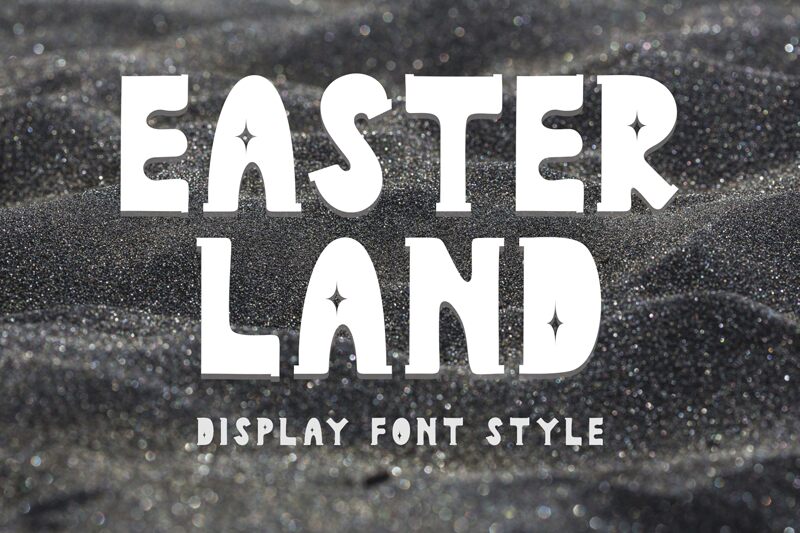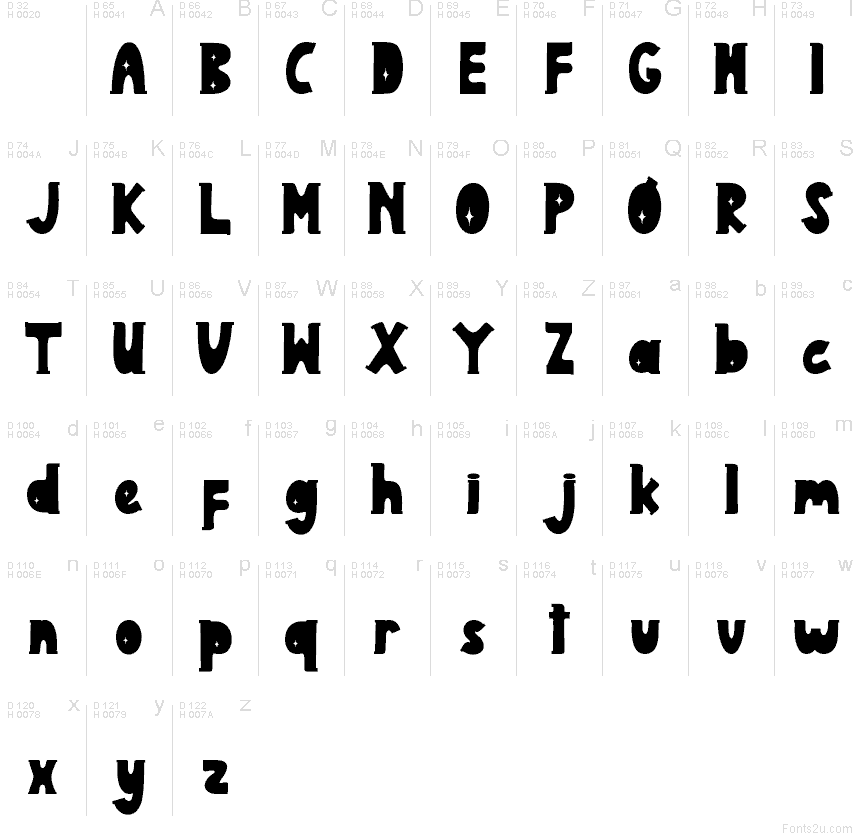
Easter Land
Easter Land de Yoga Letter es una tipografía display gratuita ideal para Pascua. Sus letras redondeadas y gruesas, junto con pequeños cortes en forma de estrella, le dan un toque decorativo y estacional muy especial. Sus formas suaves y compactas, con un estilo artesanal, están pensadas para destacar en frases festivas en lugar de usarse en textos largos.
Easter Land funciona de maravilla en tarjetas de Pascua, pósteres de primavera, invitaciones, etiquetas para manualidades infantiles y cartelería de temporada, ya que su diseño transmite el espíritu festivo sin necesidad de decoraciones extra. Esta fuente gratuita también es perfecta para gráficas en redes sociales, etiquetas de productos y titulares, especialmente cuando quieres que el propio texto sea el protagonista del mensaje de Pascua.